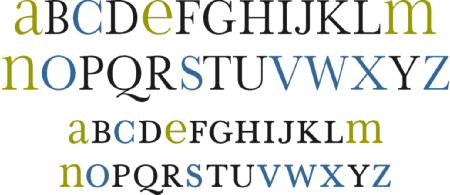
Bradbury Thompson (1911-1995)Um dos mais influentes designers gráficos na América do pós-guerra.
Depois de estudar no Washburn College (Topeka, Kansas), em 1934, começou a trabalhar em várias agências gráficas, antes de se mudar para Nova Iorque. Os seus trabalhos para a revista Westvaco Inspirations tiveram um grande impacto de 1939 a 1961. Para esta publicação, pedia imagens já usadas a agências de publicidade e a museus, para usar os fotólitos de quadricromia sobrepostos, assim conseguindo cores compostas a baixo preço. Thompson explorava formas largas, redondas, orgânicas e geométricas, que usava para unir força gráfica e simbólica nos seus spreads.
Alphabet 26A proposta de BT para simplificar e melhorar o alfabeto, chamada Alphabet 26, foi apresentada na edição Westvaco Inspirations 180, em 1950. Um só glifo para cada letra - sem distinção de minúsculas e maiúsculas.